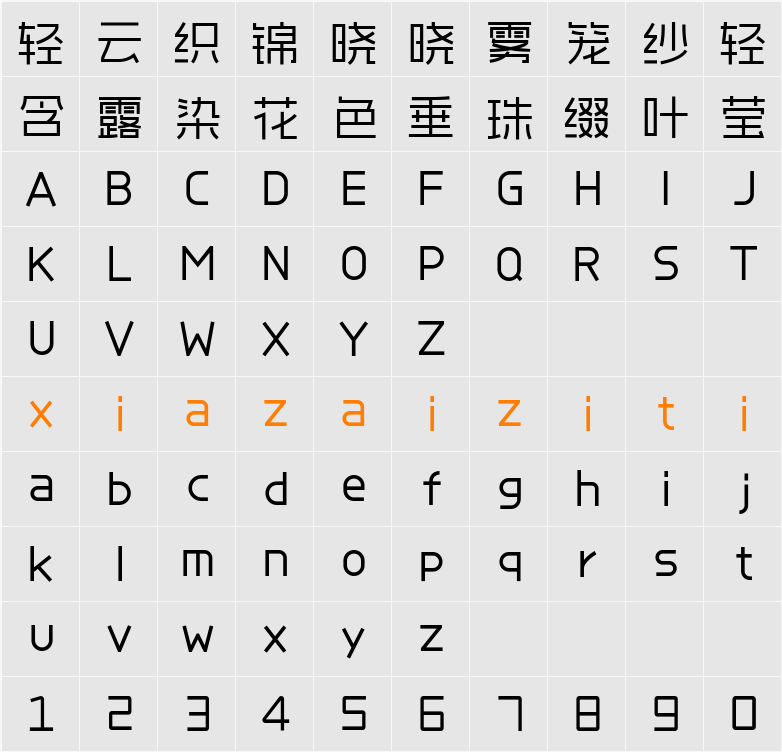
爱点风雅黑
爱点风雅黑,这款字体结构工整、笔画清晰,兼顾美观与易读性,适用于标题、正文、海报、包装、LOGO 等多种场景。字形优雅稳定,风格百搭耐看,适配日常排版与创意设计,让文字呈现更舒适、更具质感。爱点风雅黑一笔一画,皆是细节,以均衡的比例、流畅的线条打造舒适视觉体验,字形端正大气,风格简约现代。无论是商业设计、品牌宣传还是日常排版,都能轻松驾驭,让文字更有格调与力量。爱点风雅黑字体下载。
• 设计师: 李文达、陈嘉如